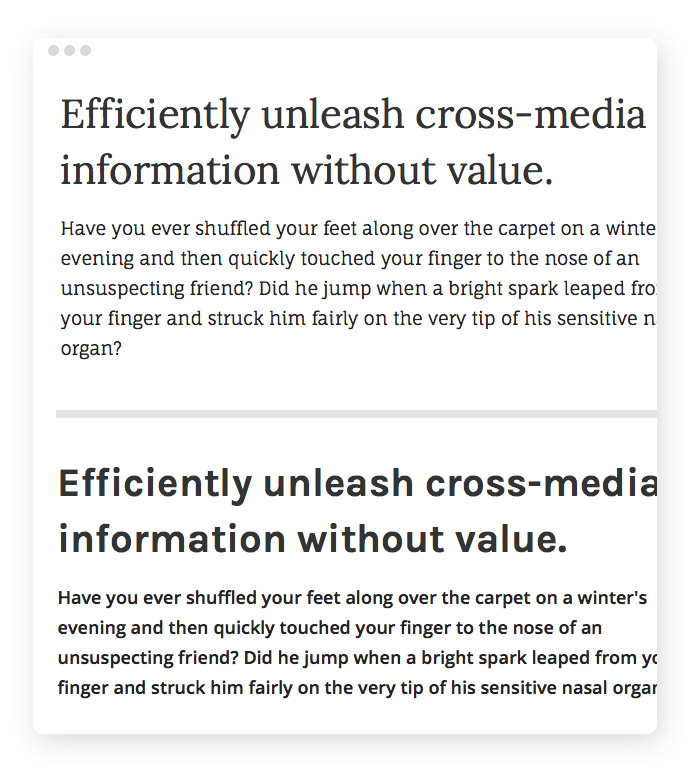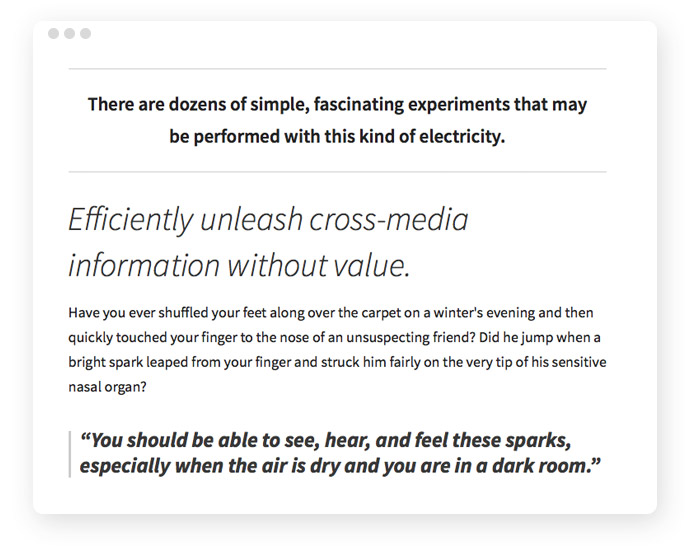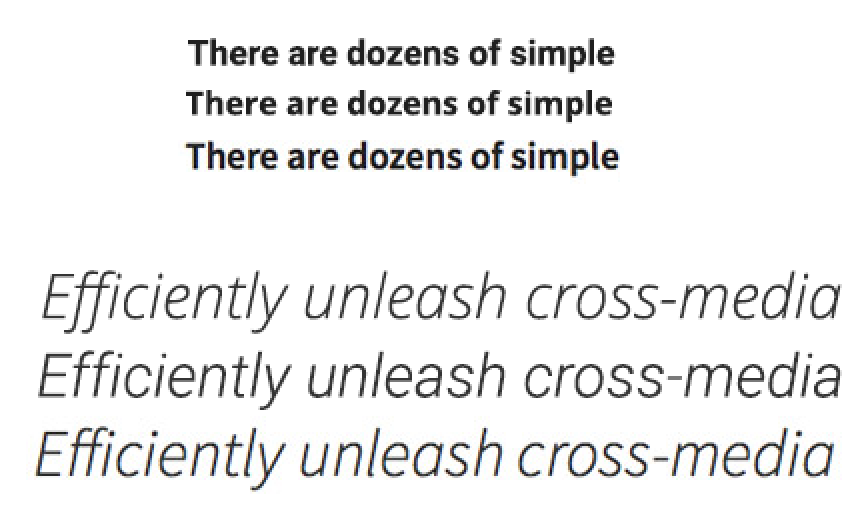
Schriftkombinationen: Regeln, Beispiele und Tipps, wie du Fonts passend kombinierst
Die Wahl der Schriftarten sollte mit Bedacht erfolgen. Die Lesbarkeit und Wirkung der Website hängen nicht zuletzt davon ab. Lerne, wie du Schriftarten kombinieren kannst, die gut zusammenpassen.
Die Wahl der Schriftarten ist eine entscheidend für den Erfolg der Website. Denn die typografische Gestaltung beeinflusst erheblich die Wirkung des Designs und sorgt für die Lesbarkeit des Textes.
Im Idealfall ist diese so gut, dass der Text einfach und entspannt gelesen werden kann. Sie sorgt für eine klare Inhaltsgliederung, sodass der Text zuerst schnell überflogen werden kann und wichtige inhaltliche Elemente optisch betont werden.
Diese Aspekte hängen ganz entscheidend von der Wahl der Schriftart(en) ab.
Schriftarten zu kombinieren ist eine Kunst, die die Lesbarkeit und die visuelle Wirkung einer Website entscheidend prägt. Durch die gezielte Auswahl und Abstimmung von Schriften können Struktur, Stimmung und Botschaft einer Seite optimal vermittelt werden – immer im Einklang mit Thema und Zielgruppe.
In diesem Artikel zeige ich dir einige Tipps, worauf du achten solltest, wenn du Schriftarten kombinierst. Praktische Beispiele veranschaulichen die Empfehlungen.
Was sind Schriftkombinationen?
Schriftkombinationen sind die gezielte Auswahl und Kombination verschiedener Schriftarten, um Lesbarkeit, Ästhetik und die gewünschte Stimmung einer Website zu optimieren. Durch harmonische Kontraste und typografische Feinabstimmung lassen sich Inhalte klar strukturieren und visuell ansprechend präsentieren.
In diesem Artikel erfährst du, wie du passende Schriftmischungen findest und typische Fehler vermeidest – mit praktischen Tipps, Beispielen und Tools zur Unterstützung.
Früher war die Auswahl aus einer Handvoll guter Systemschriften sehr überschaubar. Dank der Webfonts hat der Webdesigner inzwischen eine annähernd große Auswahl wie vormals nur die Printdesigner.
Doch wer die Wahl hat, hat die Qual. Welche aus hunderten von Schriften für das aktuelle Projekt nehmen? Lieber auf Sicherheit setzen und die „üblichen Verdächtigen“ wählen oder doch lieber ein „Zeichen setzen“ und eine markantere seltener eingesetzte Schriftart verwenden? Mit Serifen oder ohne?
Beispiele für Schriftkombinationen
Die Websitebeispiele zeigen wie unterschiedlich und aussagekräftig Schriften und die Typografie an sich wirken kann.
Die Wahl der Schriftart ist harte Arbeit.
Und oft wird ja nicht nur eine einzige Schriftart gesucht, sondern zwei oder gar noch mehr. Dann kommt es also nicht nur darauf an, ob die Schrift zum aktuellen Thema passt, sondern ob die Schriftarten auch miteinander gut wirken.
Wie lassen sich diese effektiv auswählen und Schriftarten kombinieren?
Wenn man kein typografisches Naturtalent ist (und wer ist das schon?) und kein Typedesigner, der sich den ganzen Tag nur mit Schriften und ihren Wirkungen auseinandersetzt, dann gibt es ein paar Richtlinien, an denen man sich orientieren kann.
Im Folgenden habe ich sieben Methoden zusammengestellt, die dir dabei helfen können, passende Schriftarten zu finden. Sie sind eine Art Grundlage, auf der du aufbauen kannst, um deine eigenen typografischen Erfahrungen zu machen. Vieles in der Typografie ist nämlich Intuition, Gefühl und Erfahrung.
Thema, Marke & Zielgruppe:
Den Kontext beachten
Zu Beginn der Schriftwahl sollte eine Kurzanalyse erfolgen: Um welches Thema dreht sich die Website? Welches Unternehmen oder Produkt wird präsentiert? Welche Assoziationen möchten diese vermitteln? Welche Wirkung soll das Screendesign erzeugen?
Soll das Design mehr verspielt, klassisch, trendy, dezent, frisch, minimalistisch, elegant, stilvoll, sportlich oder … wirken? Hier hilft auch das Branding und Image des Unternehmens /Projektes. Wofür steht es, was möchte es ausdrücken, wie möchte es wahrgenommen werden. Eine Anwaltskanzlei möchte anders auftreten, als bspw. ein Tattoo-Studio – dies wird sich auch in der Auswahl der Schriften widerspiegeln.
Diese Assoziationen helfen schon bei der ersten Auswahl der möglichen Schriftarten. Denn auch Schriften können bestimmte Assoziationen hervorrufen. An den unteren beiden Beispielen kann man sehr plakativ die unterschiedlichen Wirkungen der Schriftwahl erkennen.
Ein Visuelles Vokabular​ hilft dir passende Attribute für deine Designs zu finden und die Designrichtungen klar beschreiben und benennen zu können.
Unterschiedliche Schriftkombinationen, unterschiedliche Wirkungen
Vier Websites mit ganz unterschiedlichen Wirkungen, die nicht zuletzt durch die Typografie erzeugt werden.
Die Wahl der richtigen Schriftarten beginnt nicht erst mit der ästhetischen Beurteilung, sondern mit einer grundlegenden Frage: Welche Werte und Emotionen soll dein Design transportieren? Die Antwort darauf liegt im Branding. Deine Marke definiert sich durch eine bestimmte Persönlichkeit – modern und minimalistisch, verspielt und kreativ oder vielleicht edel und luxuriös? Genau diese Eigenschaften sollten sich auch in der Typografie widerspiegeln.